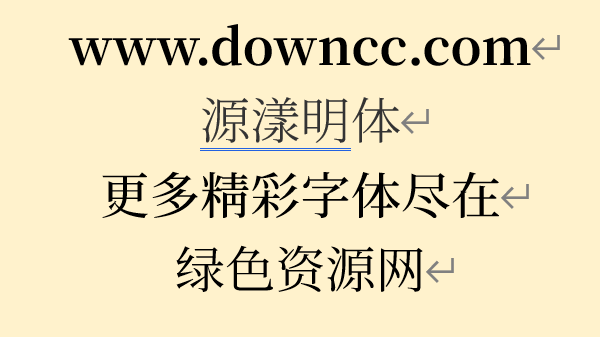
源樣明體字體不僅將文字進(jìn)行個(gè)性化處理,而且標(biāo)點(diǎn)符號(hào)也進(jìn)行了改變。該字體一共7種字重,讓你在使用的時(shí)候有更多的選擇。字體使用也是非常方便的。如果你需要?dú)g迎下載!
源樣明體字體粗細(xì)適中,字形端正大方得體,包括了Bold、extralight、heavy、light、medium、regular、semibold等7種線條不一的字體
1、傳統(tǒng)印刷體
思源宋體預(yù)設(shè)的臺(tái)灣版本(TW)采用教育部標(biāo)準(zhǔn)字體,雖然適合教育用途,但不盡符合傳統(tǒng)印刷體審美觀。例如點(diǎn)、挑、撇筆畫(huà)太多,文件排列時(shí)的的跳動(dòng)感較大。此專案采用KR版本的字符為主,較接近傳統(tǒng)印刷體習(xí)慣,排列感較為整齊。本專案并沒(méi)有造新的字符,所有字符都是來(lái)自思源宋體本身。所以KR版本未收錄的罕用字或簡(jiǎn)化字,仍然會(huì)是TW、CN風(fēng)格。
2、漢字不缺字
保留思源宋體所支援之所有漢字(包或日、韓文漢字與簡(jiǎn)體字),一般會(huì)用到的漢字幾乎不會(huì)有缺字問(wèn)題。同時(shí)也保留了所有日文假名。(但刪除了高達(dá)1萬(wàn)字的韓文字,有效降低字型檔大小。)本專案并沒(méi)有造新的字符,簡(jiǎn)體字等當(dāng)然會(huì)是CN風(fēng)格。
3、標(biāo)點(diǎn)符合繁體中文習(xí)慣
直接使用思源宋體KR版本排中文,會(huì)有標(biāo)點(diǎn)置於左下的問(wèn)題。此版本的標(biāo)點(diǎn)符號(hào)仍采用繁體中文習(xí)慣,逗號(hào)、句號(hào)等都置於正中央。并且系統(tǒng)能正確識(shí)別為繁體中文字型。
另外,思源宋體的標(biāo)點(diǎn)符號(hào)如「,」「?!乖O(shè)定有比例寬度的壓縮字寬,在illustrator、Indesign等環(huán)境下預(yù)設(shè)會(huì)壓縮50%顯示。這往往會(huì)讓標(biāo)點(diǎn)顯得過(guò)窄。此版本移除了部分符號(hào)的壓縮字寬資訊,讓這些標(biāo)點(diǎn)符號(hào)字寬原則上保持全形。